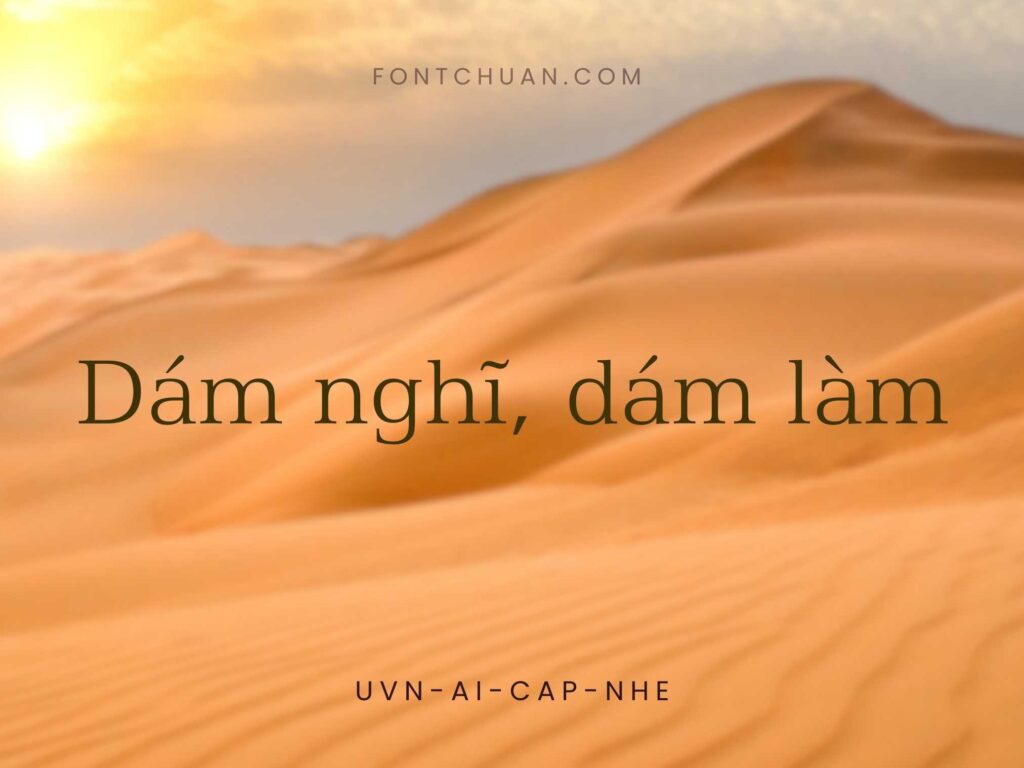
Font UVN Ai Cap Nhe Việt Hóa
UVN Ai Cập Nhẹ là một phông chữ serif thanh lịch, mang phong cách cổ điển với các đường nét mềm mại và tinh tế. Được thiết kế với sự cân đối và độ tương phản vừa phải, font này mang lại sự sang trọng và chuyên nghiệp cho các ấn phẩm in ấn và thiết kế đồ họa. UVN Ai Cập Nhẹ hỗ trợ đầy đủ bảng mã tiếng Việt, giúp người dùng tại Việt Nam dễ dàng ứng dụng trong các dự án sáng tạo của mình.
Với đặc điểm nổi bật là các đường nét thanh thoát và dễ đọc, UVN Ai Cập Nhẹ phù hợp cho nhiều ứng dụng khác nhau như in sách, thiết kế tiêu đề, poster, ấn phẩm quảng cáo và thương hiệu. Trong các sự kiện, font này có thể được sử dụng cho các dịp trang trọng như lễ hội văn hóa, sự kiện giáo dục hoặc ngày Nhà giáo Việt Nam. Ngoài ra, nó cũng thích hợp cho các ngành nghề như quảng cáo, giáo dục và in ấn.